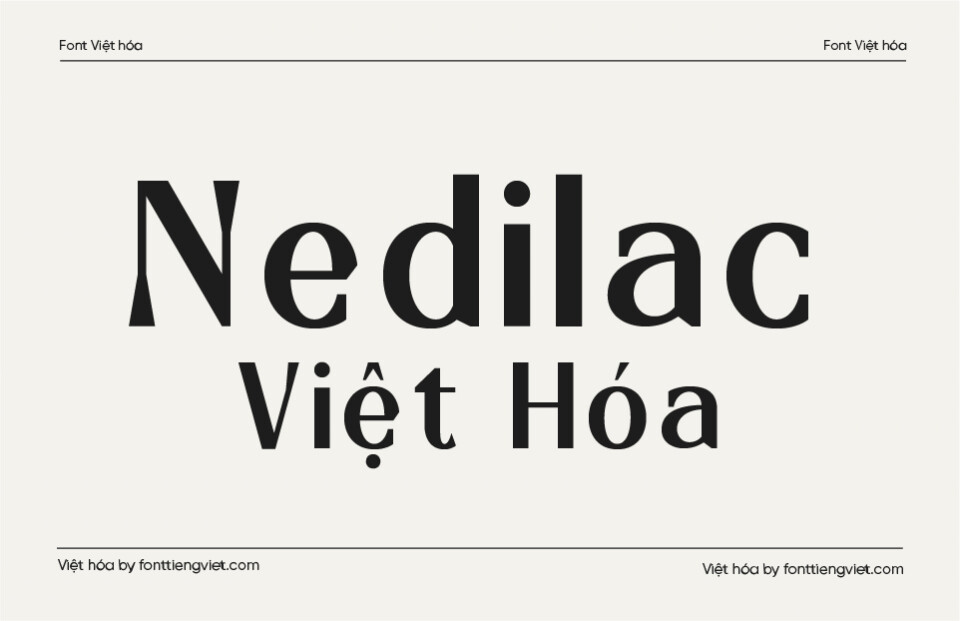
Tải Font Việt hóa 1FTV VIP Nedilac miễn phí thiết kế sang trọng đẳng cấp Giới thiệu về Font Việt hóa 1FTV VIP Nedilac trong thiết kế hiện đại Trong thế giới sáng tạo đồ họa ngày nay việc lựa chọn một bộ chữ phù hợp đóng vai trò then chốt giúp truyền tải thông điệp hiệu quả. Font Việt hóa 1FTV VIP Nedilac nổi lên như một lựa chọn hàng đầu cho các nhà thiết kế đang tìm kiếm sự kết hợp hoàn hảo giữa nét cổ điển và hơi thở hiện đại. Đây là bộ Font Miễn Phí được tinh chỉnh kỹ lưỡng về dấu tiếng Việt giúp người dùng không còn lo lắng về lỗi hiển thị khi soạn thảo văn bản hay làm banner quảng cáo. Với đường nét thanh mảnh nhưng vô cùng chắc chắn bộ chữ này mang lại cảm giác chuyên nghiệp và uy tín cho mọi sản phẩm mà nó xuất hiện. Đặc điểm nổi bật của bộ Font Việt hóa 1FTV VIP Nedilac Lý do khiến Font Việt hóa 1FTV VIP Nedilac trở nên thịnh hành chính là tính đa dụng cao trong nhiều hoàn cảnh khác nhau. Bộ font này sở hữu các đường cong mềm mại ở những góc chữ cái tạo nên sự thanh thoát nhưng vẫn giữ được cấu trúc hình khối rõ ràng. Đặc biệt hệ thống ký tự dấu được thiết kế đồng nhất về độ dày và vị trí đảm bảo tính thẩm mỹ cao nhất cho tiếng Việt. Điều này rất quan trọng đối với các bạn học sinh và giáo viên khi cần tạo ra các bài thuyết trình sinh động hoặc các tài liệu giảng dạy trực quan mà không mất quá nhiều thời gian chỉnh sửa thủ công từng ký tự dấu. Ứng dụng thực tế của Font Việt hóa 1FTV VIP Nedilac trong đời sống Không chỉ giới hạn trong lĩnh vực đồ họa chuyên nghiệp bộ chữ này còn được ứng dụng rộng rãi trong các hoạt động hàng ngày của nhà trường và doanh nghiệp. Font Việt hóa 1FTV VIP Nedilac cực kỳ phù hợp để làm tiêu đề cho các cuốn tạp chí thời trang thiệp mời sự kiện cao cấp hay thậm chí là menu cho các nhà hàng sang trọng. Đối với lĩnh vực giáo dục các thầy cô có thể sử dụng bộ font này để thiết kế bằng khen giấy khen hoặc các bảng tin nội bộ nhằm tăng thêm phần trang trọng và thu hút sự chú ý của học sinh giúp môi trường học tập trở nên mới mẻ và đầy cảm hứng hơn. Lưu ý khi sử dụng Font Việt hóa 1FTV VIP Nedilac cho người mới Mặc dù đây là một bộ chữ rất đẹp nhưng để phát huy tối đa hiệu quả người dùng cần lưu ý một số nguyên tắc cơ bản. Thứ nhất hãy ưu tiên sử dụng Font Việt hóa 1FTV VIP Nedilac cho các đoạn văn bản ngắn hoặc tiêu đề lớn thay vì các đoạn văn bản dài vì tính trang trí của nó có thể gây mỏi mắt nếu đọc quá lâu. Thứ hai việc kết hợp bộ chữ này với các font không chân (sans-serif) đơn giản sẽ tạo nên một sự tương phản tuyệt vời làm nổi bật nội dung chính. Hãy luôn kiểm tra khoảng cách giữa các chữ cái (kerning) để đảm bảo văn bản trông cân đối và chuyên nghiệp nhất có thể trên mọi thiết bị hiển thị. Hướng dẫn cài đặt và kết luận về bộ font chữ đẹp Việc sở hữu bộ chữ này cực kỳ đơn giản giúp bạn nâng tầm dự án cá nhân chỉ trong vài thao tác chuột. Sau khi tải về bạn chỉ cần giải nén và cài đặt trực tiếp vào hệ thống máy tính để sử dụng trên các phần mềm như Word Photoshop hay Canva. Tổng kết lại Font Việt hóa 1FTV VIP Nedilac là một công cụ đắc lực không thể thiếu trong kho tài nguyên của bất kỳ ai yêu thích cái đẹp và sự chỉn chu. Nếu bạn đang tìm kiếm một giải pháp Typography chất lượng hãy truy cập ngay vào Font Miễn Phí, Font Việt Hóa, Font Việt hóa 1FTV VIP Nedilac để trải nghiệm sự khác biệt. Chúc bạn có những sản phẩm sáng tạo tuyệt vời và đầy ấn tượng với bộ font chữ đặc sắc này trong tương lai gần.
Font Việt hóa 1FTV VIP Nedilac